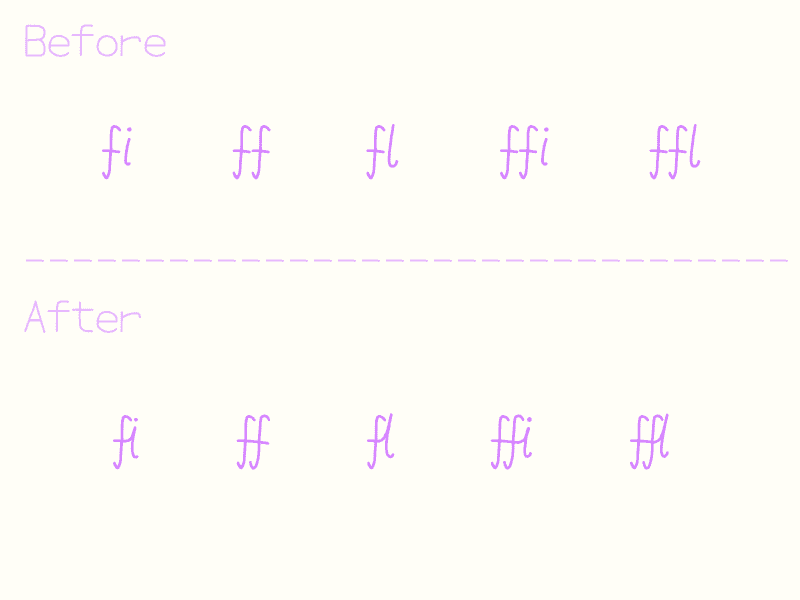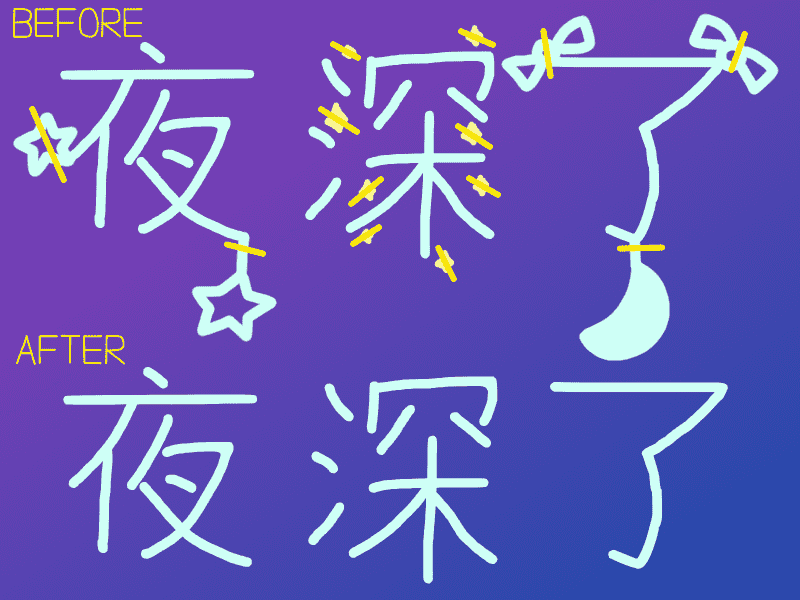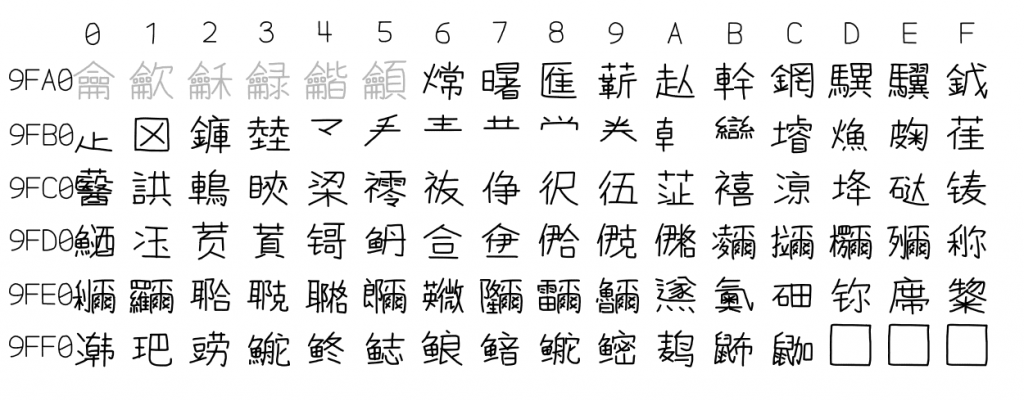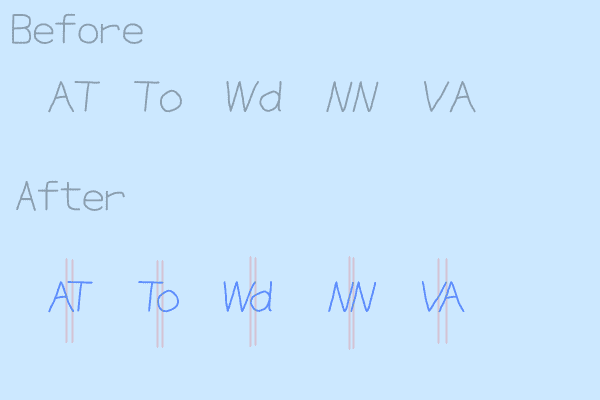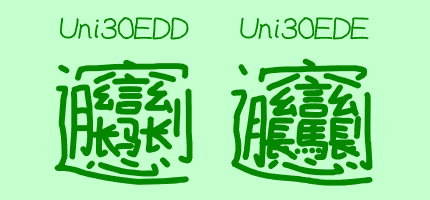
快去写作业CJK是B站UP主@派对大魔王制作的一款免费商用手写字体。这款字体于2020年7月开始秘密制作,一直肝了2万多字。快去写作业字体风格就像用小学生用圆珠笔写的字,风格可爱。
本字体最大的特点就是里面的绝大部分字形均由鼠标绘制。目前已对CJK统一汉字区块(20989个字)、谚文音节(常用2350个)提供主要支持, 可以为简繁中文、日语、韩语、英语、希腊语、俄语、泰语(仅字符)、阿拉伯语(待改进)等部分语言提供基本显示。
特色
连字(好像也不能算什么特色吧) 通过.liga脚本,fi、ff、fl、ffi、ffl这五个组合将会被连接在一起。
拒绝一切装饰 为使字符更容易被辨认,拒绝任何字符上的装饰,一目了然。 (注:变音符号不能算装饰,在实际应用中,您依然可以对字符进行装饰,但不是直接修改字体源文件。)
支持CJK统一汉字区块最后面的一些汉字 位于Uni9FA6~Uni9FFC的“神秘汉字”在此字体被支持。
Kerning 调节字符间距 基本技术,通过添加Pair Adjustment来调整字偶距。(后续会添加更多)
biang 在电脑端按住Alt,输入200413(简体)或 200414(繁体),即可召唤。Unicode位置分别为Uni30EDD、Uni30EDE。
还可能会有更多特色呈现。